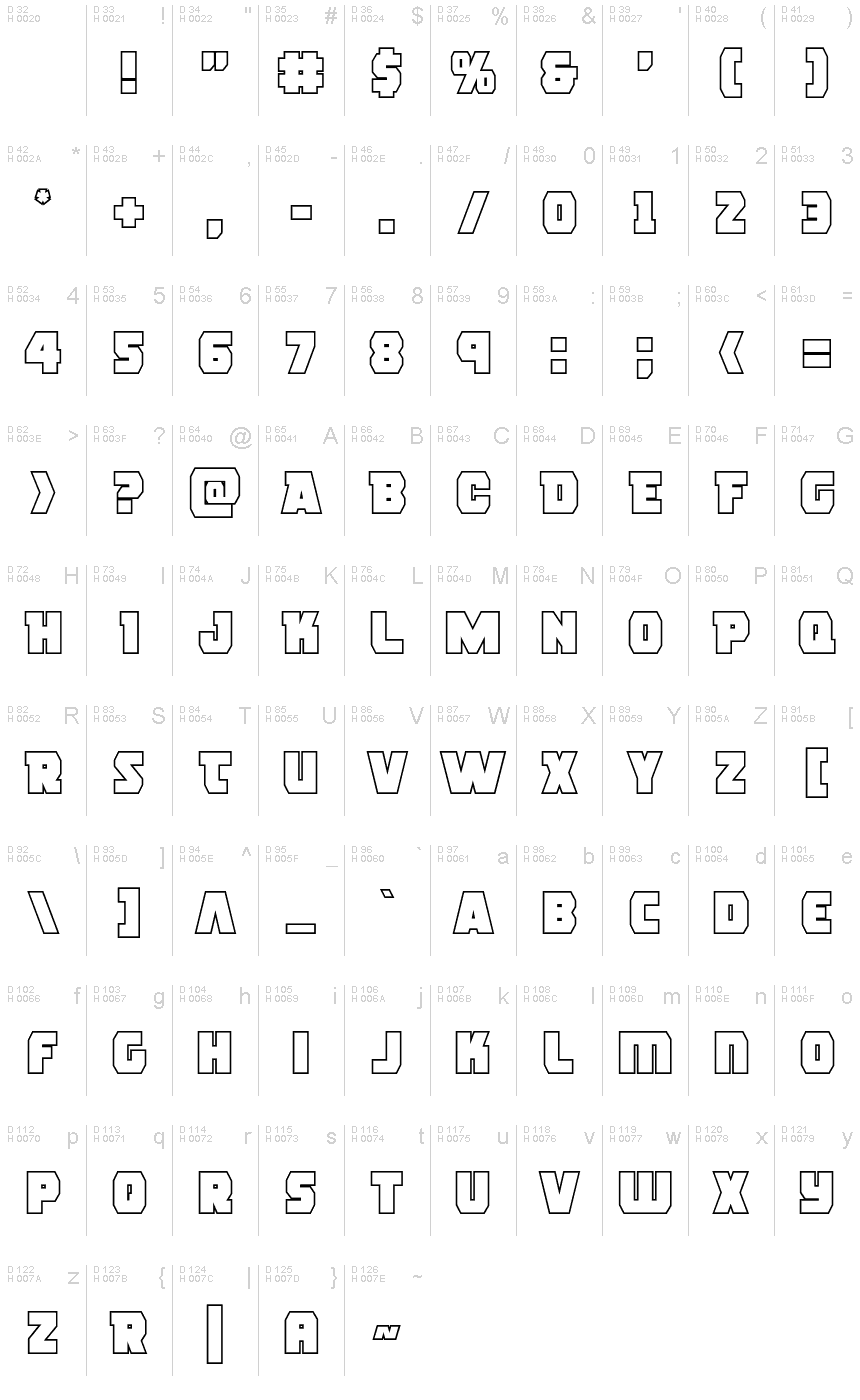
Rogue Hero Outline
Rogue Hero Outline von Iconian Fonts ist eine kostenlose, konturierte Techno-Schriftart (Caps) mit einer stumpfen, gepanzerten Silhouette. Die Buchstaben wirken wie aus dicken Platten geschnitten und nutzen gerade Kanten, abgeschnittene Ecken und geräumige Innenformen, um einen comicartigen Sci-Fi-Look zu erzeugen, der zwar mutig ist, aber nicht überladen wirkt.
Sie eignet sich am besten dort, wo ein Titel mechanisch und heldenhaft wirken muss: Spiele-Logos, E-Sport-Branding, Plakatüberschriften, Comic-Cover und Titelkarten passen perfekt zu dieser kostenlosen Schrift. Durch die offene Kontur bleiben die Großbuchstaben grafisch und lassen sich leicht schichten, sodass sie sich auch gut für Monogramme, Merchandise-Logos und kurze Cover-Zeilen eignen, die einen soliden, futuristischen Rahmen benötigen.
Version 2 ist eine vollständige Neugestaltung der Schriftart.